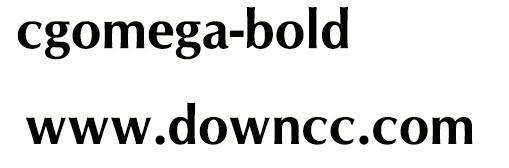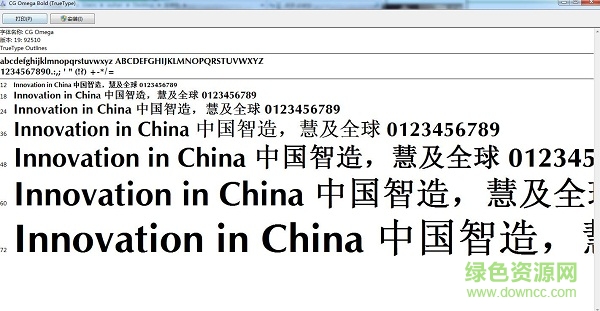
cg omega bold字體是一款生動(dòng)有神的英文字體,字體結(jié)構(gòu)恰當(dāng),弧線具有張力,結(jié)體優(yōu)美,適合用在手冊(cè)、雜志、書籍報(bào)紙等各個(gè)領(lǐng)域,喜歡的朋友快來下載吧!
【書法淵源】
兩種字母結(jié)構(gòu)不同,源于他們不同的書寫方式。不論字體是否分為襯線體或者無(wú)襯線體,他們都是根據(jù)不同的書寫方式而來。
【視覺平衡】
我們把所有字母在視覺上保持水平對(duì)齊,但是我們發(fā)現(xiàn)他們并沒有絕對(duì)意義上的相同高度。比如,這個(gè)三角形比矩形要高,否則,三角形肯定會(huì)看上去比矩形要小。而創(chuàng)造一種字體,你當(dāng)然想要所有的字母。